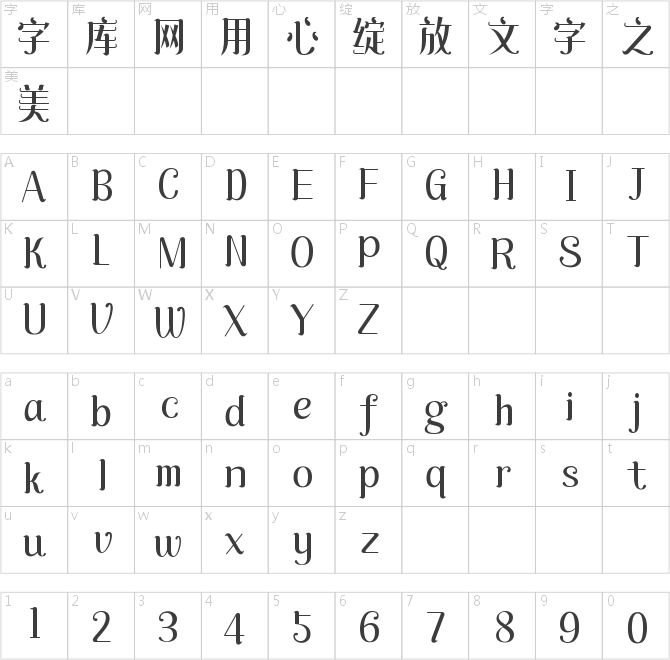
造字工房妙妙常規(guī)體 詳情頁(yè)
造字工房妙妙常規(guī)體字體字庫(kù)是一款讓人賞心悅目、百看不厭的中文字體,適合各類(lèi)廣告和產(chǎn)品包裝設(shè)計(jì)應(yīng)用,字體大小5.76MB,格式為ttf字體,上傳用戶是多喝燙水,作者/版權(quán)方為造字工房